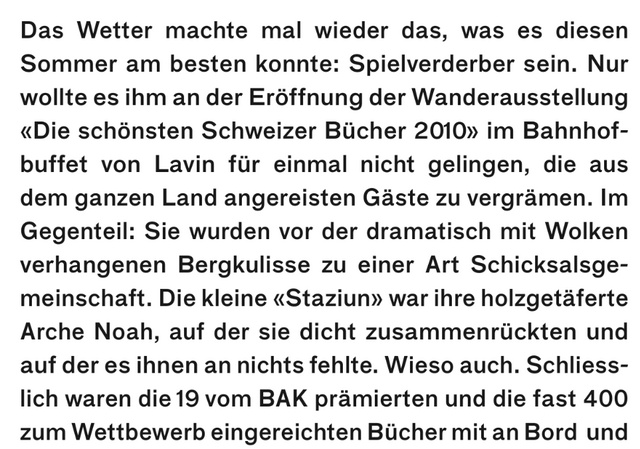
F Grotesk für lange Fließtexte
Zur ersten Frage:
8000 Zeichen ergeben keine sehr große Textmenge. Für ein Magazin ist deshalb auch eine Serifenlose, wie die F Grotesk, geeignet.
Zweite Frage:
Die F Grotesk finde ich persönlich besser und auch interessanter als die FF Bau.
Eine eher zufällig beschnipselte Helvetica (F Grotesk) finde ich als Fließtextschrift ungeeignet, besonders in einem zu fetten Schnitt.
Ohne den Kontext der Gestaltung und des Inhalts des Magazins ist so eine Frage natürlich schwer zu beantworten. Es kommt ja vor allem darauf an, was DU mit der Gestaltung erreichen willst.
Ganz persönlich als Leser gehen mir diese Ich-bin-die-coole-neutrale-Kunstkatalog-Schrift-Dinger eher auf den Keks. Sie sind natürlich lesbar, aber eben nicht so lesefreundlich wie echte humanistische Fließtextschriften. Ob es dann FF Bau, Akzidenz Grotesk oder F Grotesk ist, spielt dann auch keine wesentliche Rolle.
Die F Grotesk geht auf eine Bleisatzschrift aus dem Jahre 1880 der Schriftgiesserei Schelter & Giesecke zurück. Also nichts mit Helvetica-Beschnipsel. Dein Kommentar finde ich schlichtweg nutzlos.
Es mögen Details sein zwischen der AG und der F Grotesk aber sie machen ein Schriftbild aus, darum habe ich ja das Thema eröffnet.
Die F Grotesk geht auf eine Bleisatzschrift aus dem Jahre 1880 der Schriftgiesserei Schelter & Giesecke zurück.
Dann sind die FF Bau und die F Grotesk auf der gleichen Grundlage entstanden: der Schelterschen Grotesk. Es ist also eher eine Geschmacksfrage, welche der beiden Schriften du vorziehst. Für eine Magazingestaltung würde ich eher zur Bau tendieren, da sie in meinen Augen etwas ruhiger läuft.
Ich weiß ehrlich gesagt nicht, was du dir als Antwort erhoffst, wenn du allgemein fragt »was haltet ihr von ...« ohne genauer Kontext und Intention deiner Gestaltung zu spezifizieren.
Die unterschiedlichen Digitalisierungen mögen mal etwas rauer mal etwas harmonischer sein – welches davon Deinem Zweck am nächsten kommt, können wir nicht wissen oder eben nur in Form eines persönlichen Geschmacks ausdrücken.
Deine Kritik kann ich angesichts der folgenden Antworten nicht ganz nachvollziehen, denn das sind doch ganz sachliche Argumente:
Das sind für meine Begriffe alles sinnvolle Aussagen, die auf Deine Fragestellungen eingehen. Zusammengefasst sagen meine Vorredner, dass eine serifenlose Schrift durchaus geeignet sein kann, um einen längeren Fließtext zu setzen, dass sie aber in der Regel nicht so lesefreundlich ist wie echte humanistische Fließtextschriften. Und dass es in diesem Kontext eben nicht so relevant ist, welche Helvetica-ähnliche (sprich serifenlose) Schrift verwendet wird, weil es im Bezug auf die Lesefreundlichkeit keinen Unterschied macht, welche der aufgezählten serifenlosen Schriften eingesetzt wird.
Ich kann auch Deine Kritik daran, dass der Punkt »Gefallen oder Nichtgefallen« von den Kollegen berücksichtigt wurde, nicht ganz nachvollziehen, denn wenn Menschen, die täglich in ihrem professionellen Umfeld mit dem Einsatz und der Gestaltung von Schriften zu tun haben, ihre persönlichen Präferenzen für oder gegen eine Schrift äußern, dann kann man auch daraus nutzbringende Erkenntnisse ziehen. Im Zweifel kann man als Fragesteller ja einfach noch mal nachfragen, wenn man das gerne genauer ausgeführt hätte. Da Du in Deinen Fragestellungen die Formulierungen »Was haltet Ihr von …« und »Wie findet Ihr …« gebraucht hast, hätte ich Dir vermutlich genau wie die Kollegen mit einer persönlichen Einschätzung geantwortet. :-)